汉字,凝聚着独特而深厚的中华之美,是中华文化璀璨绚丽的瑰宝。在进行广告的创意,对汉字进行创意,往往也能达到比较惊艳的效果,今天就给大家带来一期干货,推荐一些常用的字体设计创意方法。
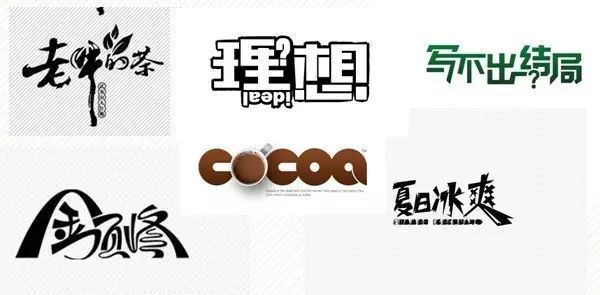
替换法。替换法是在统一形态的文字元素加入另类不同的图形元素或文字元素。其本质是根据文字的内容意思,用某一形象替代字体的某个部分或某一笔画,这些形象或写实或夸张。将文字的局部替换,是文字的内涵外露,在形象和感官上都增加了一定的艺术感染力。
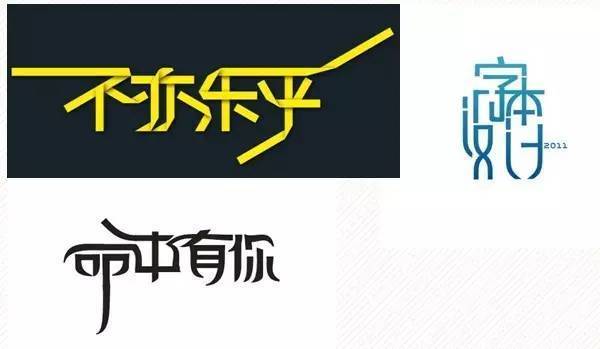
共用法。“笔画公用”是文字图形化创意设计中广泛运用的形式。文字是一种视觉图形,它的线条有着强烈的构成性,可以从单纯的构成角度来看到笔画之间的异同,寻找笔画之间的内在联系,找到他们可以共同利用的条件,把它提取出来合并为一。
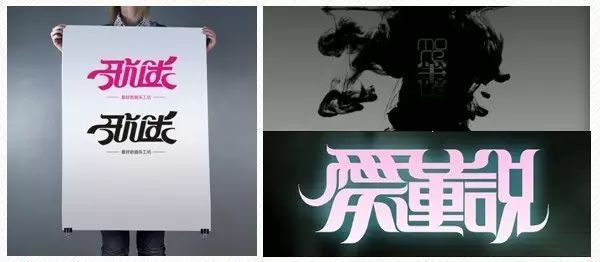
分解重构法。分解重构发是将熟悉的文字或图形打散后,通过不同的角度审视并重新组合处理,主要目的是破坏其基本规律并寻求新的设计生命。把文字图形化运用到设计中,能使作品具有强烈的视觉冲击力,更便于公众对设计者的作品主题的认识、理解与记忆。
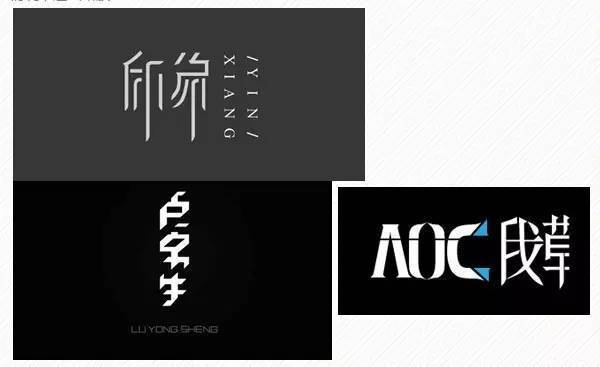
断肢法。断肢法是把一些封合包围的字,适当的断开一口出来 ,或把左边断一截,或右边去一截,体现出一些设计感。但是使用这种方法要注意一点:要在能识别的情况下适当断肢。
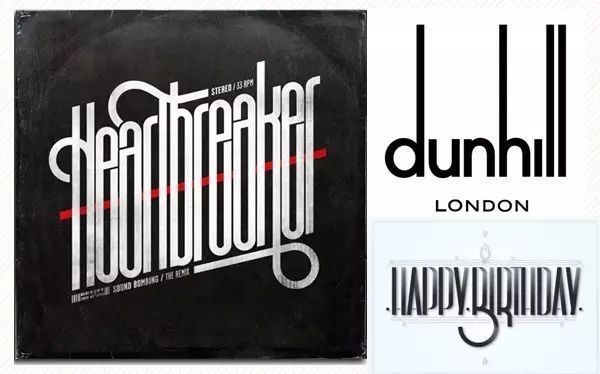
上下拉长法。这种方法是把字变细,然后上下拉长,营造出类似条形码的感觉,这样的做法可以增强艺术感和设计感。
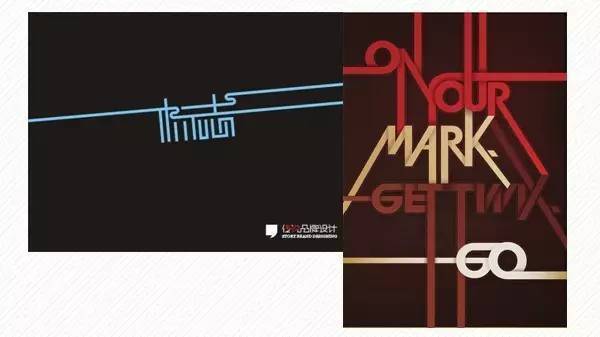
画龙点睛法(或一点拉长法)。其实这也算是拉长法的一种,找到标志中的一个点或线作为重点把他拉长,使得处理好的字体,再加一笔更是画龙点睛之作。
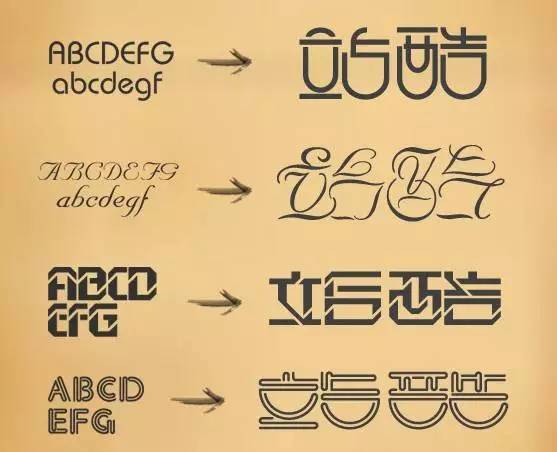
洋为中用法。这种创意方法其实很简单。首先到字库里找几个特别点的英文字体,然后找出这些字体的笔触和特征,最后就可以把这些特征运用到中文字体设计中,体现出不一样的美感。
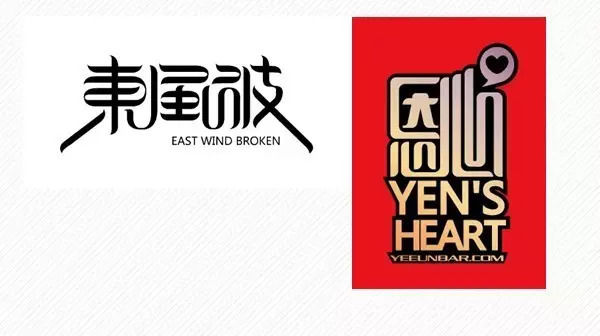
结构转变法。这种方法可以说是替代法的一种,就是把竖或横线或折换成其他比划,这样的创意方法虽然可以营造艺术感,但是字体的识别度会大大降低。
看了这么多字体设计的创意方法,你现在有没有一种灵感迸发的感觉?不妨选用其中的一种方法来设计一下你的名字吧!